Tipsy Tiger — гамбургский сервис по доставке напитков. Tipsy Tiger обещает привезти на вечеринку вино, пиво, сидр или коктейли в течение 15 минут. Для первой рекламной кампании проекта дизайнер Хосе Мануэль Вега выбрал шрифт Spektra студии Type Salon (начертание
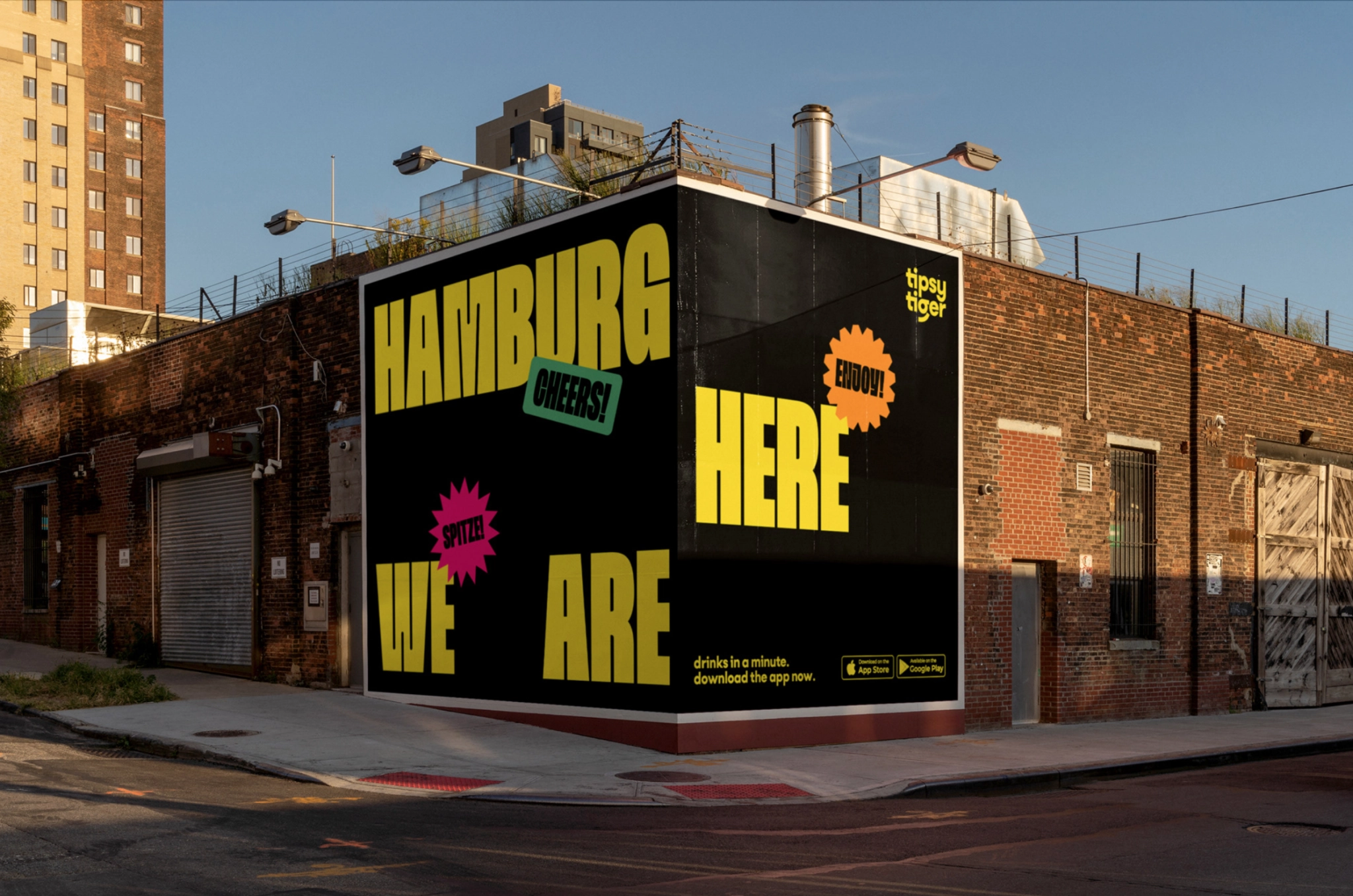
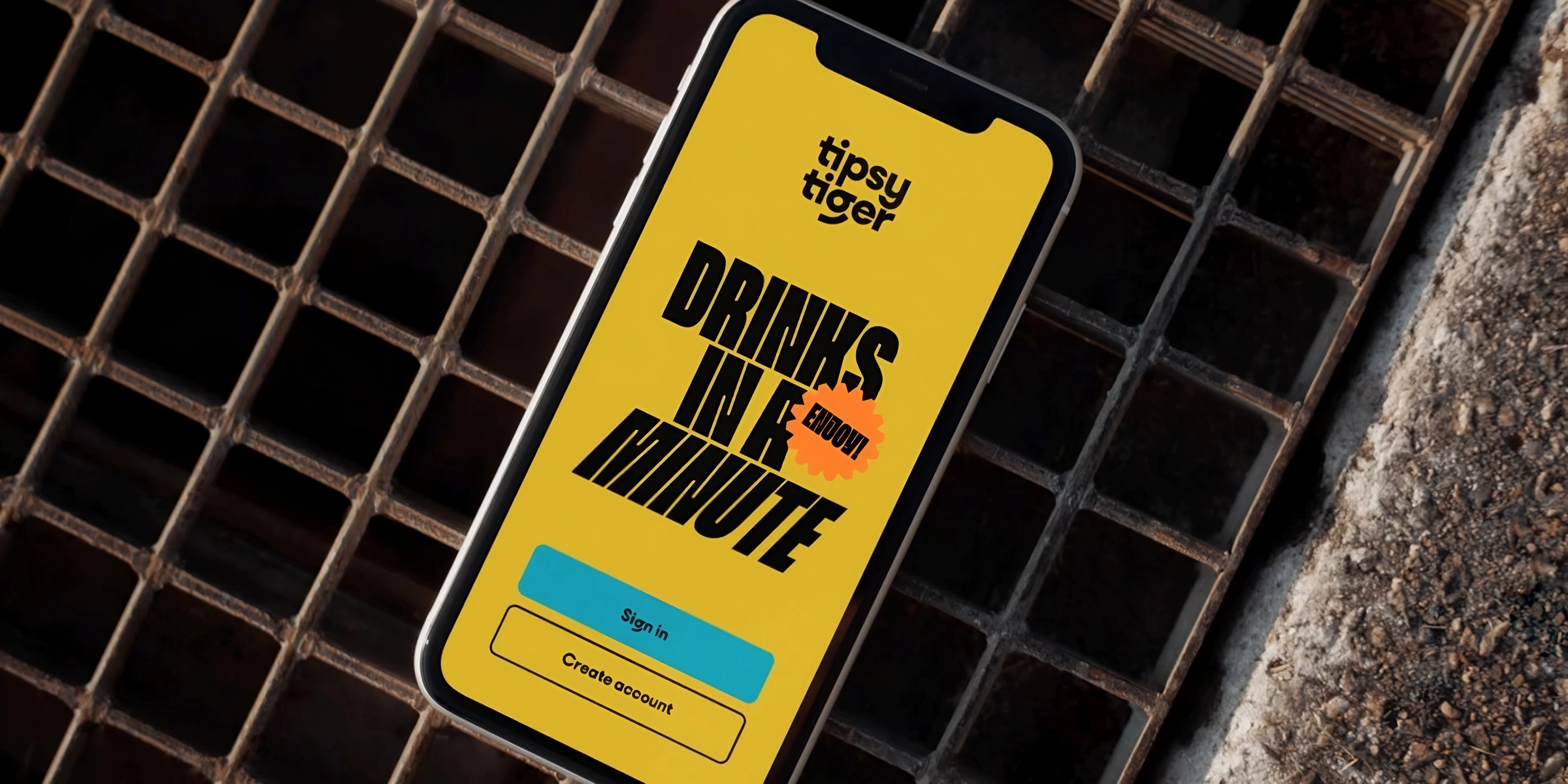
Spektra — вариативный шрифт Альи Херла и Кристы Ликар из студии Type Salon с кириллицей, греческим, арабским и ивритом. У Spektra пять начертаний — от Light до Heavy с прямым и обратным наклоном для каждого (плюс вариативный шрифт с двумя осями).